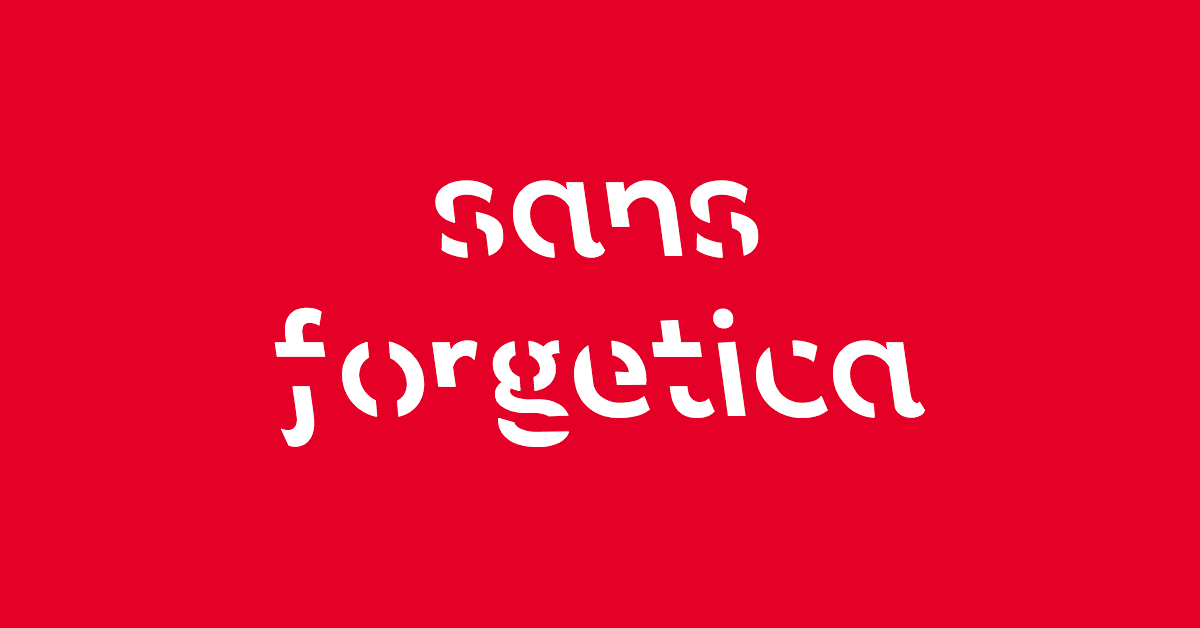
Sans Forgetica, la tipografía que te ayuda a recordar
Esta tipografía ha sido diseñada de tal manera que te ayuda a memorizar textos con mayor rapidez y facilidad.
Entre otras muchas variables, la legibilidad de las tipografías es un tema que determina el éxito o fracaso de una fuente. Su apariencia visual es un tema que preocupa a muchos diseñadores, pero las formas, además de hacer más o menos atractivo un sistema tipográfico, determinan si es funcional o no. En la actualidad, con la cantidad de información que leemos a lo largo del día, es común que no seamos capaces de recordar todos esos datos; por eso ha nacido Sans Forgetica, una tipografía que, gracias a su diseño, promete ayudarnos a memorizar mejor lo que leemos.
Sans Forgetica ha sido diseñada por un equipo multidisciplinar formado por investigadores y profesores universitarios de la Escuela de Diseño del Instituto Real de Tecnología de Melbourne (RMIT) con un enfoque eminentemente académico. Es una realidad que muchos estudiantes tienen dificultades para memorizar textos y eso se debe, en gran medida, a que nuestro cerebro procesa las palabras que leemos demasiado rápido. Sans Forgetica, con su inclinación lateral y las porciones eliminadas a cada glifo, causa una "dificultad deseada" que influye en el proceso cognitivo, emitiendo a nuestra mente la orden de llenar esos espacios vacíos, ralentizando la lectura y permitiéndonos memorizar información con mucha mayor facilidad.
El proyecto fue llevado a cabo por un equipo de profesionales y académicos australianos y en él han participado un centenar de estudiantes realizando pruebas de memoria y tests para analizar qué formas y diseños eran más eficientes a la hora de crear memoria acerca de los textos escritos con esas tipografías. El resultado es una fuente con una dificultad de lectura mayor a la habitual, pero creada con un propósito, la de ayudar a nuestro cerebro a procesar y digerir la información lentamente y así memorizarla con mayor fluidez.